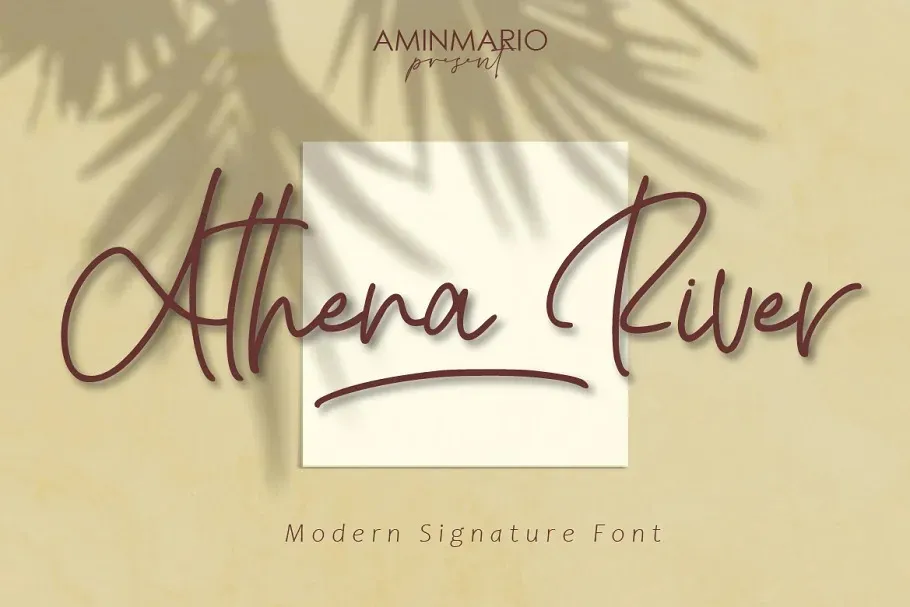
Athena River Font – Download Grátis
A Athena River Font é uma escolha perfeita para projetos que exigem um toque autêntico e pessoal. Desenvolvida pela Aminmario no formato de letra escrita a mão, esta fonte possui uma versão alternativa minúscula, alternativas minúsculas com swash, ligaturas e sublinhados para aproximar ainda mais o resultado final do estilo natural da escrita a mão. Ela foi projetada para oferecer um nível de realidade impressionante, como se você estivesse escrevendo diretamente no papel. Integram-se perfeitamente nas características OpenType, tornando-a uma opção ideal para qualquer projeto que precise de um toque de escrita à mão única. Ideal tanto para design editorial quanto para criações gráficas, a Athena River Font vai transformar seu trabalho em algo realmente especial e autêntico.